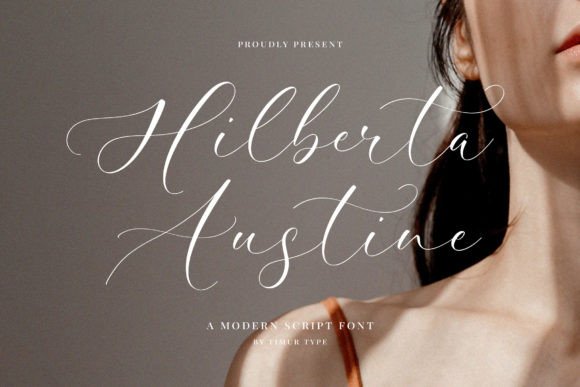
Hilberta Autstine
Att hitta rätt designelement kan vara utmanande, men Hilberta Autstine erbjuder en exceptionell samling som omedelbart lyfter ditt arbete.
Oavsett om du skapar POD-produkter (Print on Demand), bröllopsinbjudningar eller grafik för sociala medier, är Hilberta Autstine ett perfekt val.